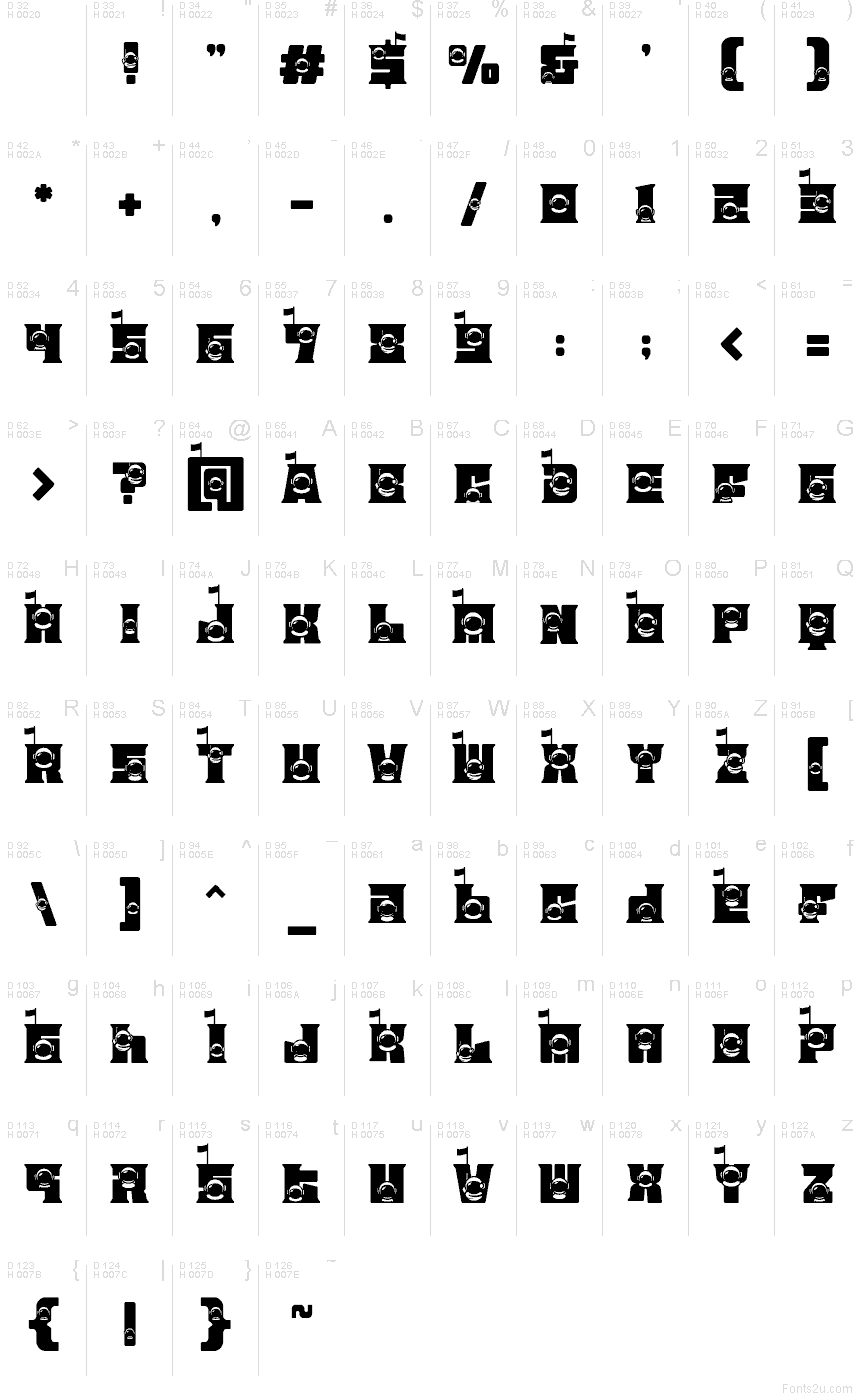
Astral Zenith One od Putracetol Studio je bezplatné písmo typu display s astrálním nádechem, které proměňuje široké černé tvary písmen v jeviště pro opakující se planetární prstence a malé vrcholky zakončené vlaječkami. Tento společný motiv dodává designu zvláštní rytmus připomínající panorama, díky čemuž každé písmeno působí spíše jako kompaktní kousek vesmírného značení než jako běžné písmo.
Nejvíce vynikne na titulcích plakátů, obalech alb, herní grafice, záhlavích akcí a tematickém zboží, kde tento planetární detail dokáže nést koncept sám o sobě. Temná hmota a vložené kruhové emblémy dodávají krátkým logům nebo názvům na obalech teatrální, nadpozemský nádech bez nutnosti dalších ilustrací.